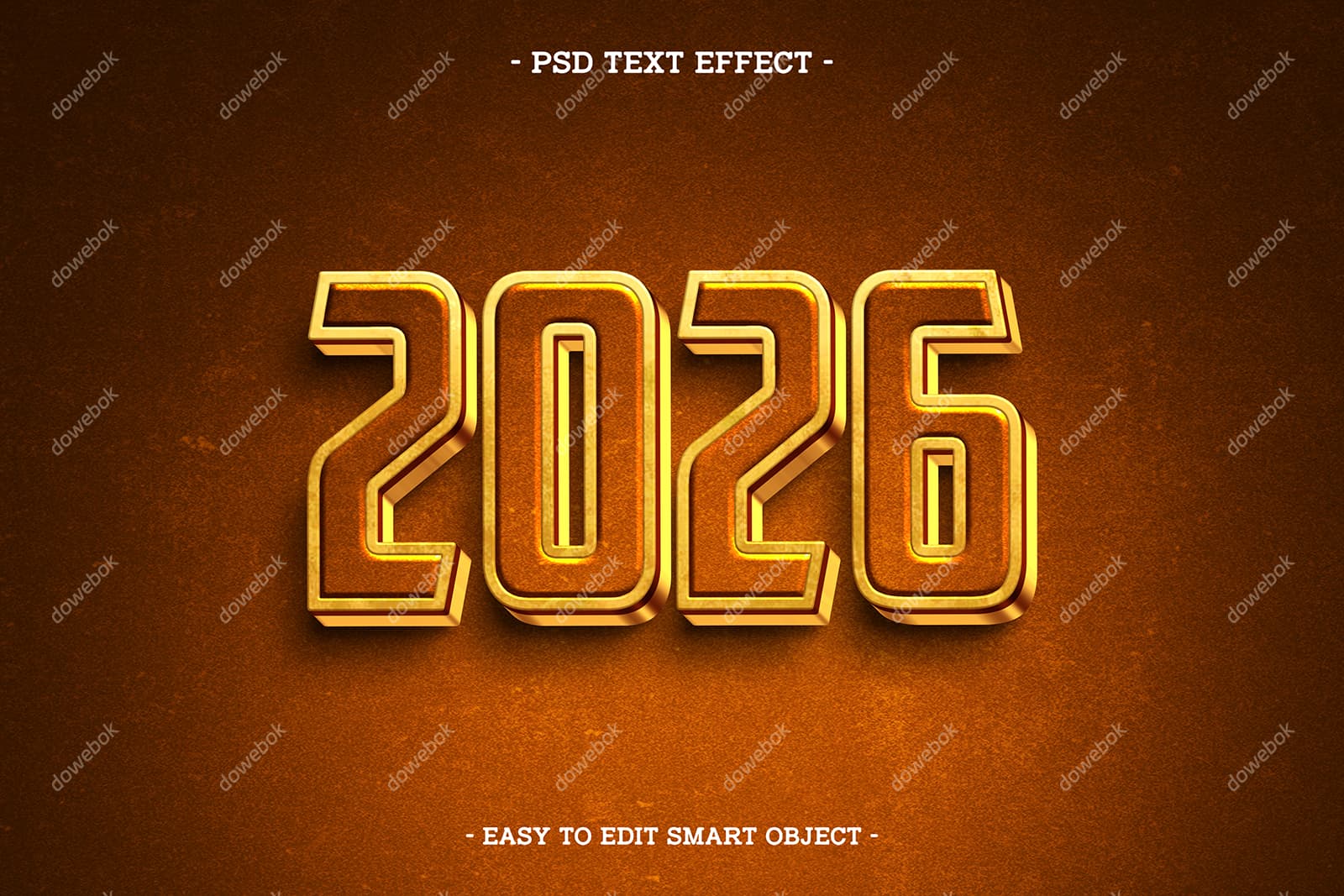
这是一款由金色立体数字设计的 2026 新年快乐 PSD 素材,暖棕纹理背景上,“2026” 以金边内嵌暖橙的立体字呈现,质感温暖且富有层次感。顶部标 “PSD TEXT EFFECT”,底部注其为可编辑素材。整体暖棕配色既显复古温馨,又借字体的立体设计添精致感,既突出字体效果的质感,也点明可编辑属性,适配暖调复古风创意海报、装饰物料等场景。
金色立体数字设计 2026 新年快乐 PSD 素材